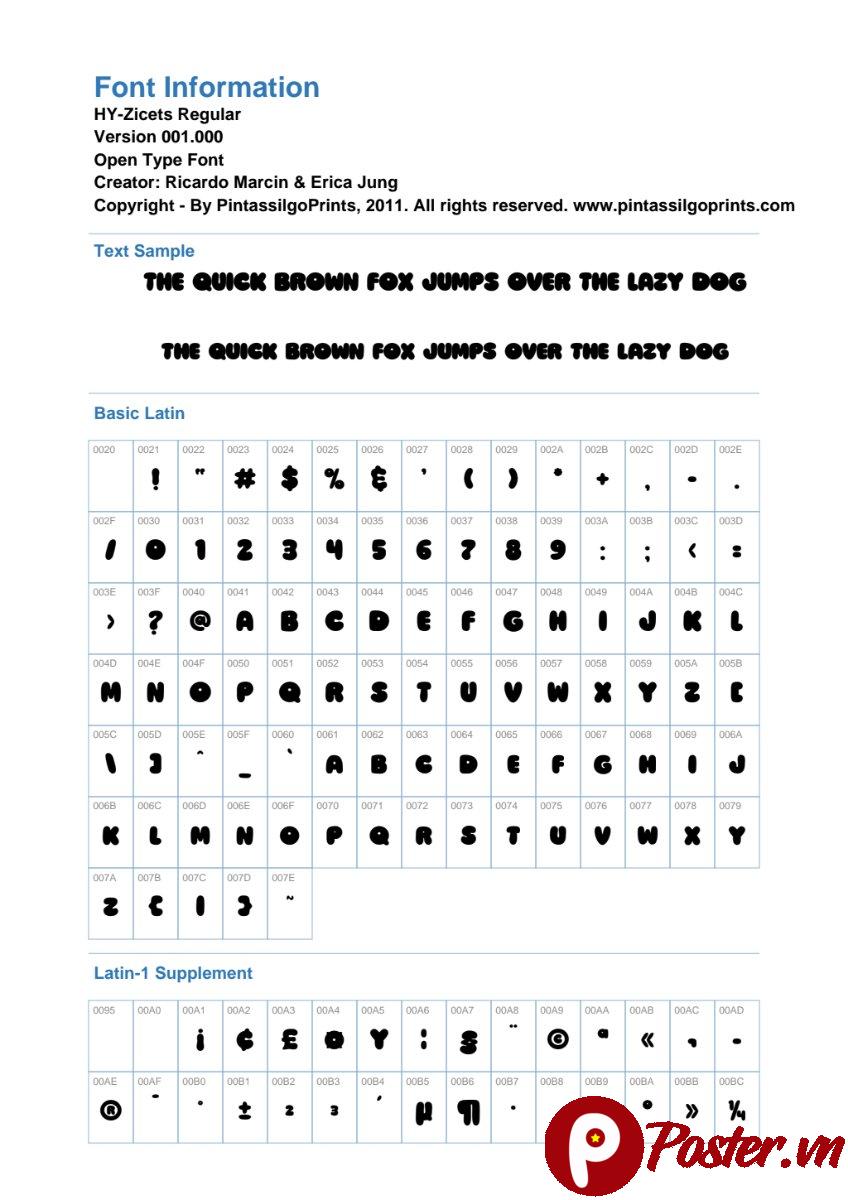
Font HY-Zicets: Độc đáo & Sáng tạo
Trong thế giới thiết kế đồ họa đầy màu sắc, việc lựa chọn một font chữ phù hợp có thể tạo nên sự khác biệt lớn cho tác phẩm của bạn. Font HY-Zicets là một lựa chọn tuyệt vời cho những ai đang tìm kiếm sự độc đáo, sáng tạo và cá tính. Với thiết kế đặc trưng, font chữ này không chỉ thu hút ánh nhìn mà còn truyền tải thông điệp một cách mạnh mẽ và ấn tượng.
Giới thiệu về Font HY-Zicets
Font HY-Zicets là một kiểu chữ sans-serif với các đường nét bo tròn, mềm mại nhưng vẫn giữ được sự mạnh mẽ và rõ ràng. Điểm đặc biệt của font này là sự kết hợp giữa nét hiện đại và một chút phá cách, tạo nên vẻ ngoài thân thiện nhưng không kém phần chuyên nghiệp. Được phát triển bởi Ricardo Marcin & Erica Jung, HY-Zicets mang đến một làn gió mới cho các nhà thiết kế, giúp họ dễ dàng tạo ra những sản phẩm nổi bật.
Đặc điểm nổi bật của Font HY-Zicets
• Thiết kế độc đáo: Các ký tự của HY-Zicets có hình dáng tròn trịa, đầy đặn, tạo cảm giác vui tươi và dễ đọc. Điều này làm cho nó trở thành lựa chọn lý tưởng cho các dự án hướng đến đối tượng trẻ em hoặc những thiết kế cần sự thân thiện, gần gũi.
• Tính linh hoạt cao: Mặc dù có phong cách riêng biệt, HY-Zicets vẫn rất linh hoạt trong việc ứng dụng. Bạn có thể sử dụng nó cho tiêu đề, logo, poster, banner, bao bì sản phẩm, hay thậm chí là các ấn phẩm truyền thông kỹ thuật số.
• Dễ đọc: Với khoảng cách hợp lý giữa các ký tự và độ dày nét chữ vừa phải, HY-Zicets đảm bảo khả năng đọc tốt ngay cả ở kích thước nhỏ, giúp thông điệp của bạn luôn được truyền tải rõ ràng.
• Hỗ trợ đa ngôn ngữ: Font này hỗ trợ bộ ký tự Latin cơ bản và Latin-1 Supplement, cho phép bạn sử dụng nó trong nhiều ngữ cảnh ngôn ngữ khác nhau.
Ứng dụng của Font HY-Zicets trong thiết kế
Với những đặc điểm nổi bật, Font HY-Zicets có thể được ứng dụng rộng rãi trong nhiều lĩnh vực thiết kế khác nhau:
Thiết kế logo và branding
HY-Zicets là một lựa chọn tuyệt vời để tạo ra các logo độc đáo và dễ nhận diện. Sự kết hợp giữa nét tròn trịa và hiện đại giúp logo của bạn trở nên thân thiện, dễ nhớ và tạo ấn tượng mạnh mẽ với khách hàng. Đặc biệt phù hợp cho các thương hiệu trong ngành thực phẩm, đồ chơi trẻ em, giáo dục hoặc các dịch vụ sáng tạo.
Thiết kế poster, banner và quảng cáo
Khi cần tạo ra các ấn phẩm quảng cáo thu hút sự chú ý, HY-Zicets sẽ là trợ thủ đắc lực. Các tiêu đề được viết bằng font này sẽ nổi bật trên mọi nền, giúp thông điệp của bạn được truyền tải một cách hiệu quả. Dù là poster sự kiện, banner khuyến mãi hay quảng cáo trực tuyến, HY-Zicets đều có thể mang lại hiệu quả thị giác cao.
Thiết kế bao bì sản phẩm
Đối với các sản phẩm hướng đến đối tượng trẻ em hoặc các sản phẩm cần sự vui tươi, thân thiện, HY-Zicets là một lựa chọn hoàn hảo cho bao bì. Nó giúp sản phẩm trở nên hấp dẫn hơn, tạo cảm giác gần gũi và đáng yêu, khuyến khích người tiêu dùng lựa chọn.
Thiết kế ấn phẩm kỹ thuật số
Trong kỷ nguyên số, việc tạo ra nội dung hấp dẫn trên website, mạng xã hội hay ứng dụng di động là vô cùng quan trọng. HY-Zicets có thể được sử dụng để thiết kế các tiêu đề bài viết, infographic, hoặc các yếu tố giao diện người dùng, giúp tăng tính thẩm mỹ và sự tương tác.
Hướng dẫn sử dụng Font HY-Zicets hiệu quả
Để tận dụng tối đa vẻ đẹp của Font HY-Zicets, bạn có thể tham khảo một số mẹo sau:
• Kết hợp với font chữ khác: HY-Zicets thường phù hợp làm tiêu đề hoặc các đoạn văn ngắn. Khi sử dụng cho nội dung dài hơn, hãy cân nhắc kết hợp nó với một font chữ sans-serif hoặc serif truyền thống, đơn giản hơn để đảm bảo khả năng đọc.
• Lựa chọn màu sắc: Với phong cách vui tươi, HY-Zicets thường rất hợp với các bảng màu tươi sáng, năng động. Tuy nhiên, nó cũng có thể tạo điểm nhấn mạnh mẽ khi được sử dụng với màu sắc tương phản trên nền trung tính.
• Kích thước và khoảng cách: Thử nghiệm với các kích thước và khoảng cách chữ khác nhau để tìm ra sự cân bằng tốt nhất cho thiết kế của bạn. Đảm bảo rằng các ký tự không quá gần hoặc quá xa nhau để duy trì tính dễ đọc.
• Sử dụng trong các dự án sáng tạo: Đừng ngại thử nghiệm HY-Zicets trong các dự án đòi hỏi sự sáng tạo và phá cách. Đây là font chữ có khả năng biến hóa đa dạng, giúp bạn thể hiện cá tính riêng.